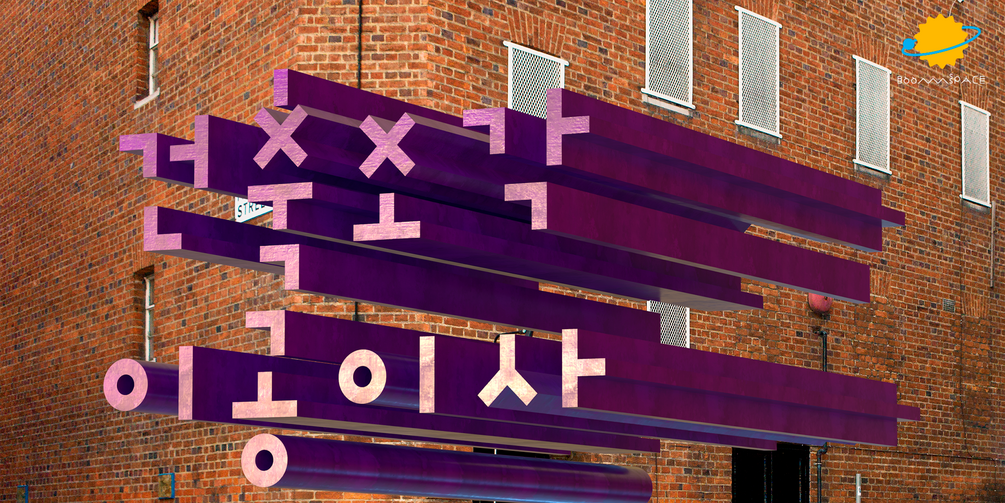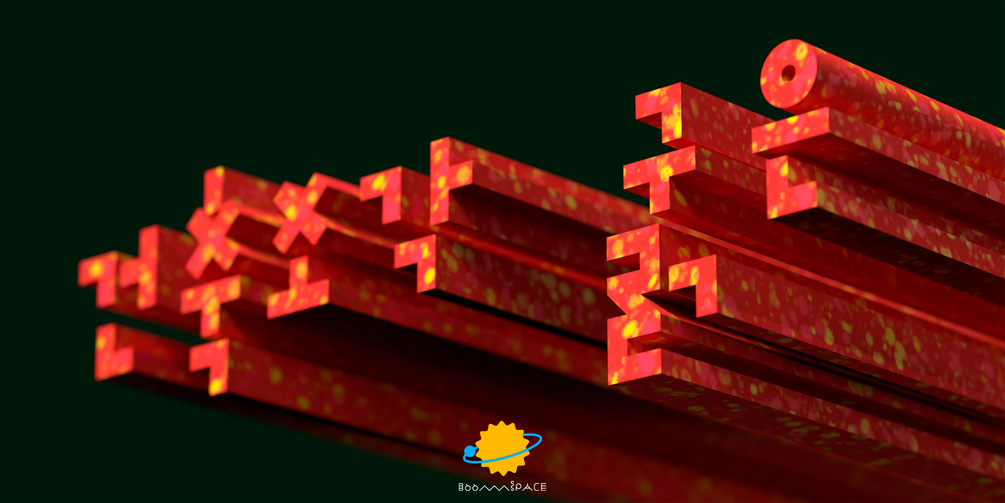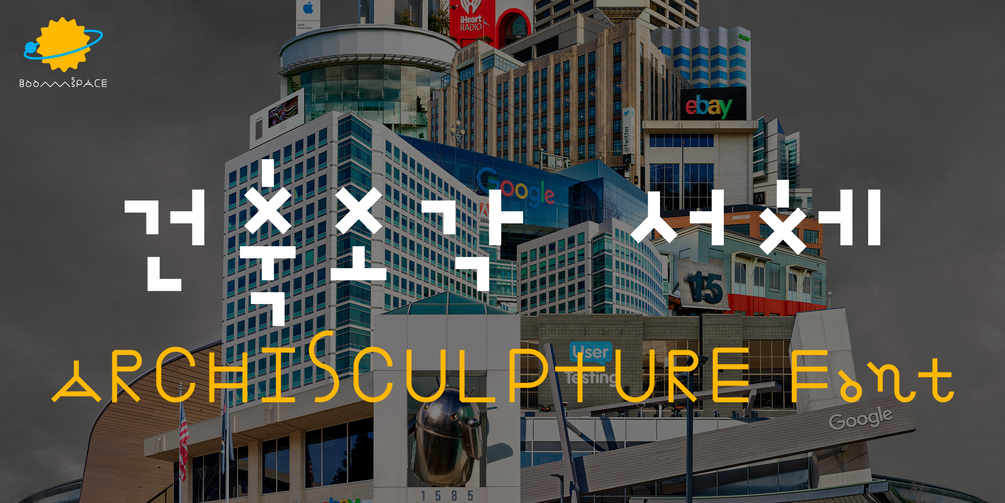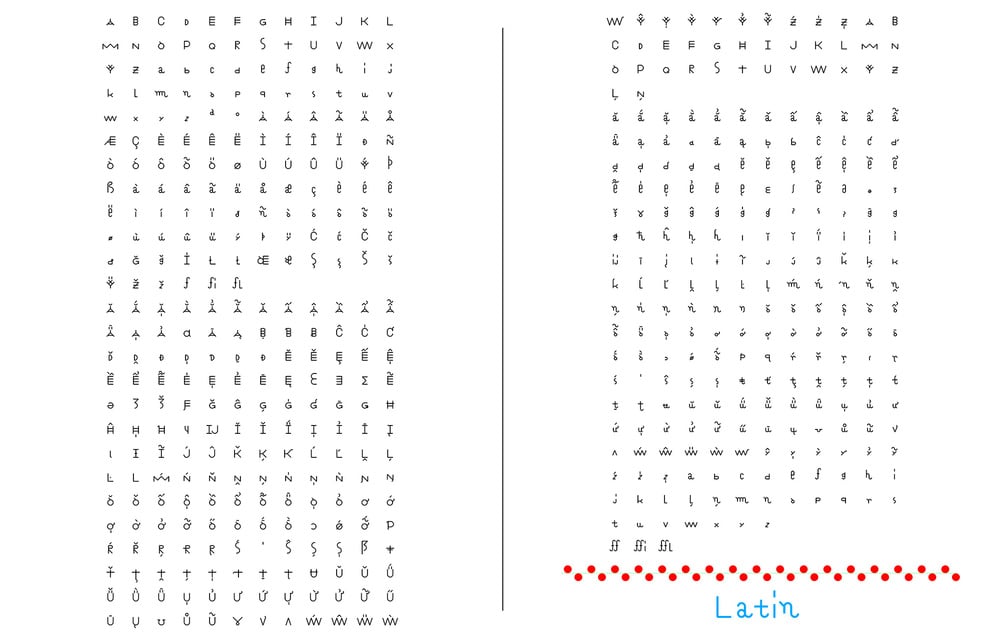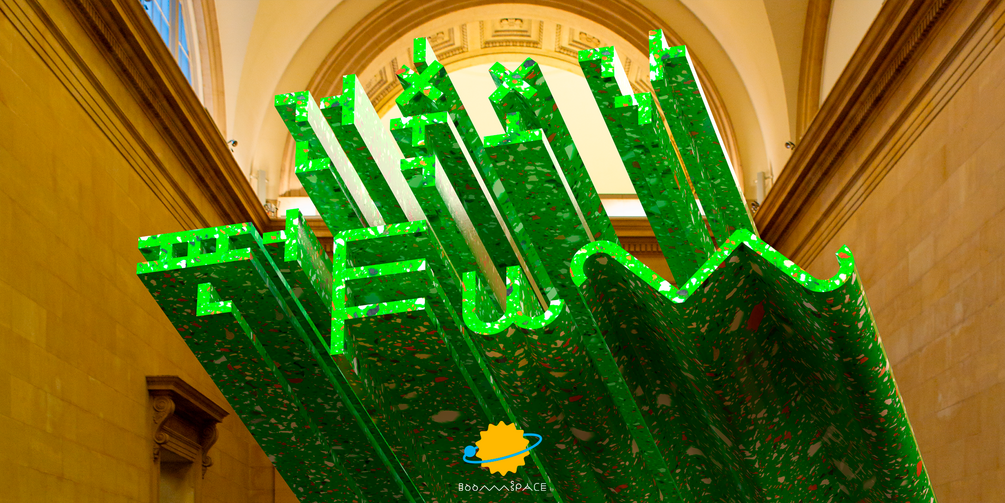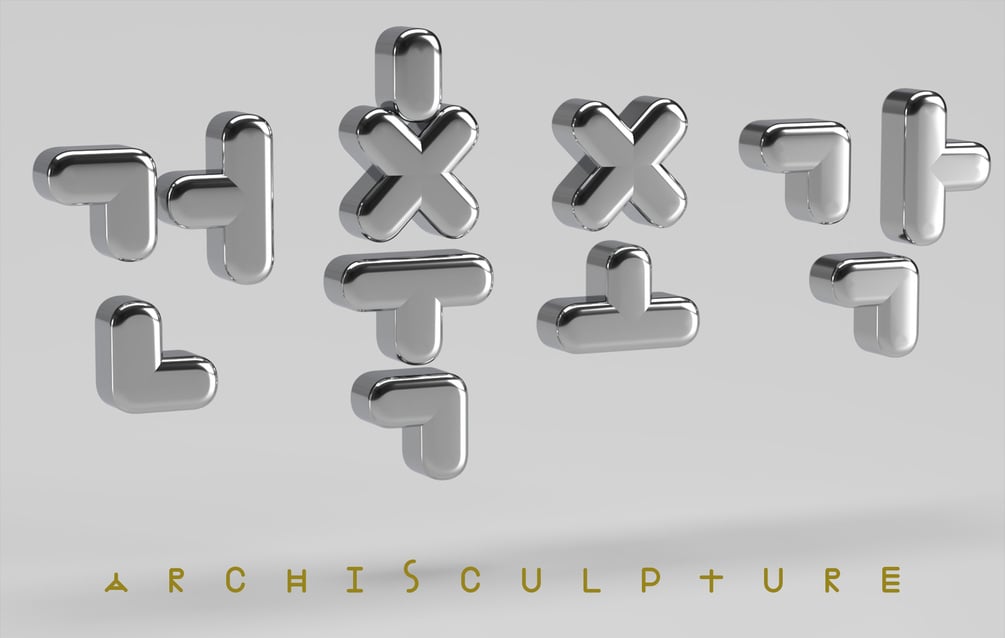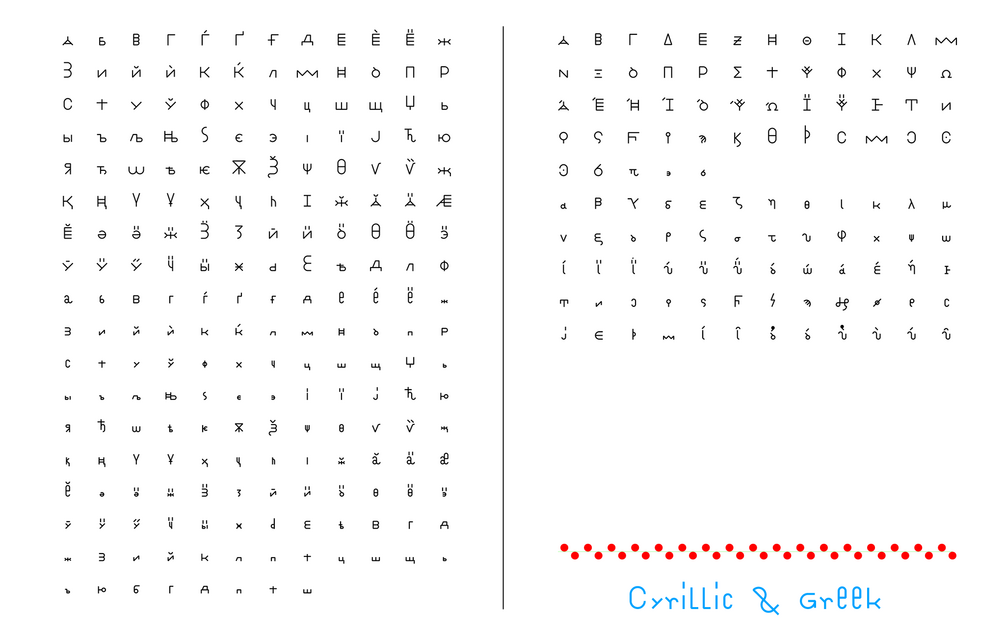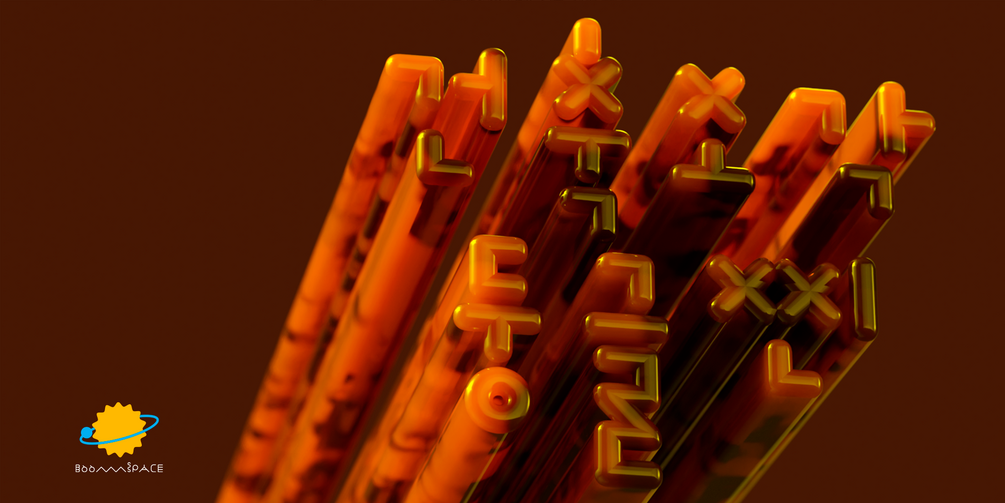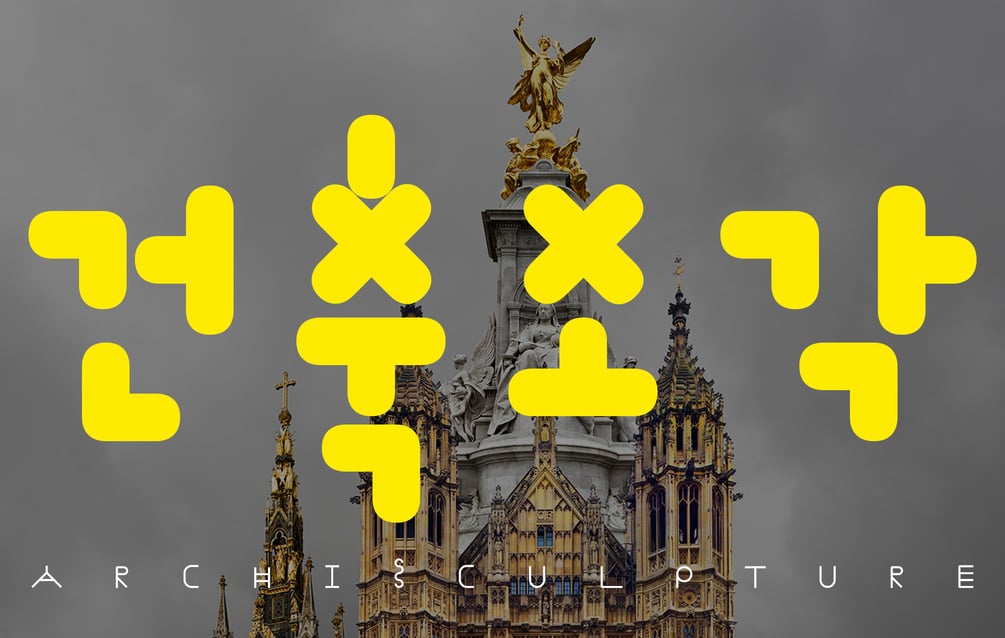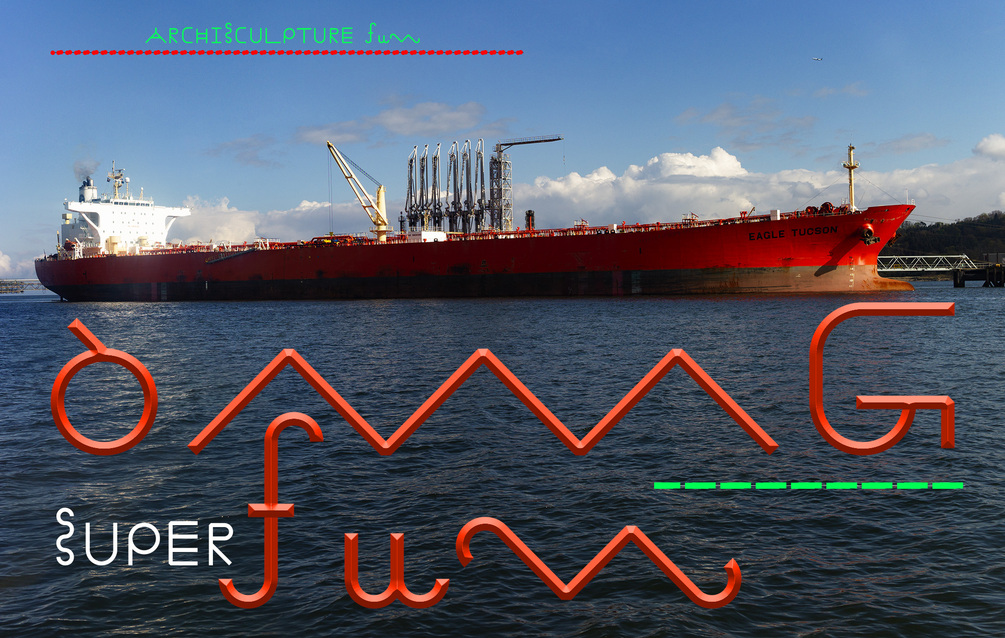
건축조각 서체 가족 6종 ARCHISCULPTURE font family - 6 fonts
건축조각 오리지널 서체 3가지 두께 비교
건축조각 오리지널 둥글찐
2022년 한글날 576돌을 기념하여 한글 서체를 만들었습니다. 글꼴은 작가 BSW의 작품 이름 중 하나를 붙여 ‘건축조각’ 서체입니다.
건축조각 서체는 건축물과 조각품 같은 구조를 지닌 컴퓨터 글자입니다. 글자 필수 모양새에 영향을 주지 않는 범위 내에서, 다양한 구조가 만들어지도록 일부러 필요하지 않은 획을 추가하기도 하며 서체를 디자인했습니다. 그 결과, 글자가 놀랍도록 변화무쌍하고, 재미있고, 독특하게 건축되었어요!
건축조각 폰트 패밀리 모든 서체는 현대 한글 11,172자, 라틴, 유럽, 그리스, 키릴, 베트남, 아라비아 숫자, 특수 문자 그리고 기호를 표현할 수 있습니다.
총 글립스 수는 13,194개입니다.
독특한 건축조각 서체로 멋진 글과 디자인을 지어보세요!
건축조각 오리지널, 건축조각 2024, 건축조각 fun 서체 비교
건축조각 폰트 패밀리에는 다음과 같은 서체가 들어 있습니다.
5. ARCHISCULPTURE2024_v150 (오리지널 서체에서 한글위치에 변화를 주었습니다)
6. ARCHISCULPTURE_fun_v150 (2024년 버전에서 라틴 ACDGLMNPSTVWmnvw 글자 디자인이 재미있게 변경되었습니다)
Thickness comparison of three ARCHISCULPTURE original fonts
ARCHISCULPTURE RoundedBlack
BSW and BOOMSPACE designed a typeface named after one of BSW's art projects, ‘ARCHISCULPTURE’.
ARCHISCULPTURE font is a computer typeface made with architectural structures. We deliberately added more strokes to the extent that it does not affect the essential components of the character, and as a result of designing the look, the typeface was constructed surprisingly kaleidoscopic, fun, and unique!
All ARCHISCULPTURE fonts contain Latin, European, Greek, Cyrillic, Vietnamese, 11,172 modern Korean characters, Arabic numerals, special characters and symbols.
The total number of glyphs is 13,194.
Create your own writings and designs with unique ARCHISCULPTURE font!
ARCHISCULPTURE original, 2024, and fun font comparison
ARCHISCULPTURE font family contains the following fonts:
5. ARCHISCULPTURE2024_v150 (this is the '2024' version of the font in which the positions of some Korean letters have been changed from the original version)
6. ARCHISCULPTURE_fun_v150 (this is the 'fun' version of the font in which the design of some Latin letters 'ACDGLMNPSTVWmnvw' has been changed from the 2024 version)